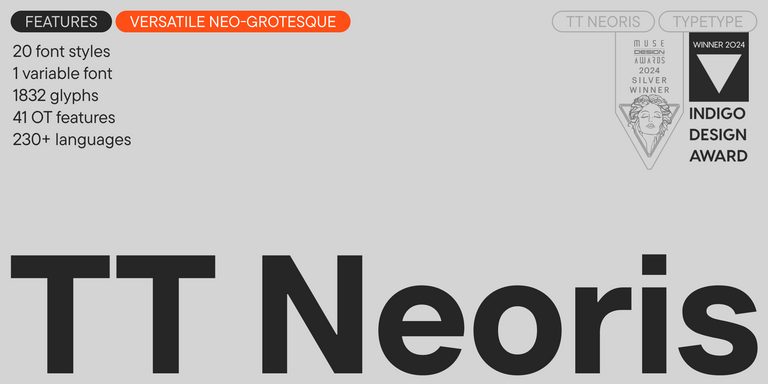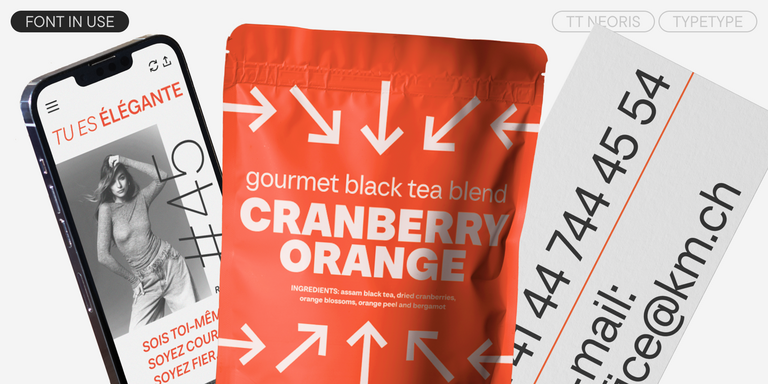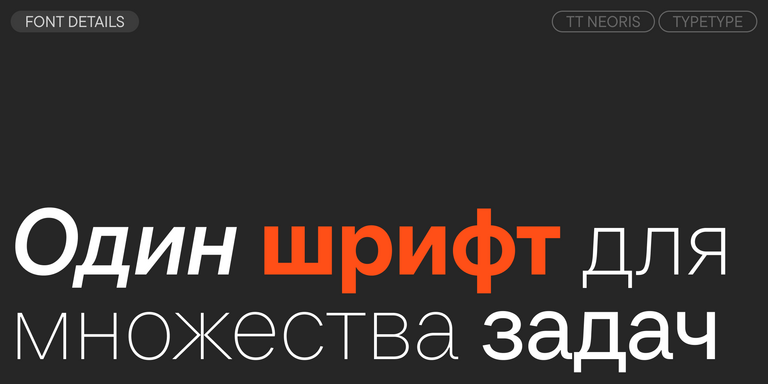
TT Polihaus — ТТ Полихаус
Произносится «ТТ Полихаус». «Polihaus» — производное от греческого «πολύς», в переводе — «много», и слова «хаос». Буквы TT являются аббревиатурой названия компании.
TT Polihaus — экспериментальный гротеск, который на первый взгляд кажется обычным, а затем разбирается на части, превращаясь в трафаретный узор.
TT Nooks Script — ТТ Нукс Скрипт
Произносится «ТТ Нукс Скрипт». «Nooks» — производное слово от nook, в переводе с английского «закоулок». «Script» произносится как «скрипт», в переводе с английского «курсив». Буквы «TT» являются аббревиатурой названия компании.
TT Nooks Script — шрифт с уникальным рисунком, который не имеет прямых аналогов.
TT Qurdisma — ТТ Курдизма
Произносится «ТТ Курдизма». Слово «Qurdisma» происходит от греческого κούρδισμα, в переводе — «извилистый». Буквы TT являются аббревиатурой названия компании.
TT Qurdisma — узкий и плотный декоративный шрифт, напоминающий причудливое растение. Вьющиеся, плавные контуры рождают растительный орнамент.
TT Neoris Pro — ТТ Неорис
Произносится «ТТ Неорис». «Neoris» — производное слово от neo («новый» с латинского) и rise («восход» с английского). Буквы «TT» являются аббревиатурой названия компании.
TT Turns — ТТ Тернс
Произносится «ТТ Тернс». «Turns» — производное слово от turn, в переводе с английского «поворот». Буквы «TT» являются аббревиатурой названия компании.
TT Turns — геометрический гротеск с акцентными круглыми знаками и выразительными нависающими элементами. Это универсальный шрифт, который лаконично выглядит и отлично читается в маленьком размере, при этом в крупных кеглях становится акцидентным и проявляет свой характер на максимум. Он энергичный, сильный и динамичный — особенно отчётливо это проявляется в наклонных начертаниях.
TT Regins — ТТ Реджинс
Произносится «ТТ Реджинс». «Regins» — производное слово от reign, в переводе с английского «царствовать». Буквы «TT» являются аббревиатурой названия компании
TT Regins — шотландская новостильная антиква с королевским характером. Яркий контраст и острые треугольные засечки придают этому шрифту строгий и властный нрав.
TT Frantz — ТТ Франтц
Произносится «ТТ Франтц». «Frantz» — имя собственное немецкого происхождения. Буквы «TT» являются аббревиатурой названия компании.
В TT Frantz можно найти небольшие отсылки в эстетике арт-деко, которые выражены в сильно заниженной или наоборот сильно завышенной талии у букв. Кроме того, в зависимости от положения ползунка регулировки оси, у некоторых букв изменяется закрытость апертуры.
TT Quaris — ТТ Кварис
Произносится «ТТ Кварис». «Quaris» — искусственно образованное слово от латинского «quartz» (кварц), и своим названием намекает на драгоценные камни. Буквы «TT» являются аббревиатурой названия компании.
TT Quaris — изысканная и современная ленточная антиква. Перед разработкой этой гарнитуры мы провели глубокое исследование архетипов ленточных антикв.
TT Ricordi Allegria — ТТ Рикорди Аллегрия
Произносится «ТТ Рикорди Аллегрия». «Ricordi» — производное слово от ricordo, с итальянского — «воспоминание», «Allegria» — в переводе с итальянского «веселье». Буквы «TT» являются аббревиатурой названия компании.
TT Ricordi Allegria — современная ленточная антиква, отличительные особенности которой, гиперболизированная разноширинность в пропорциях, контраст между штрихами, клиновидные окончания штрихов и отсутствие традиционных засечек.
TT Modernoir — ТТ Модернуар
TT Geekette — ТТ Гикетт
Произносится «ТТ Гикетт». «Geekette» — производное слово от geek (с английского «гик», человек, увлеченный технологиями) и уменьшительного женского суффикса -ette. Буквы «TT» являются аббревиатурой названия компании.
TT Geekette — вариативная антиква с дружелюбным характером. Мы ушли от упрощений сухой геометрии и поэкспериментировали с плавностью, мягкостью и пластичностью форм. А чтобы шрифт стал чуть более стильным и серьёзным, мы сделали его моноширинным.